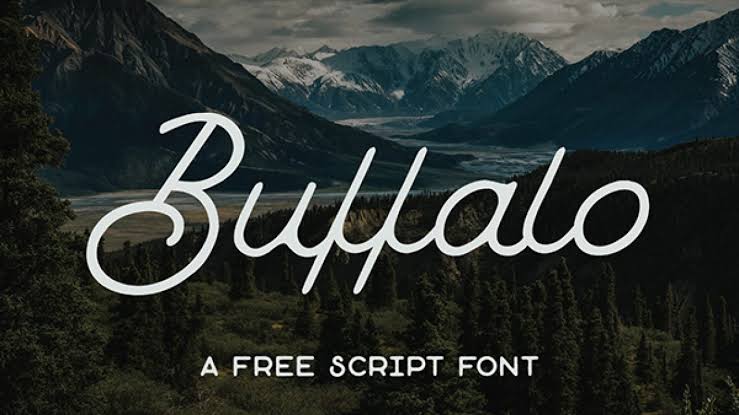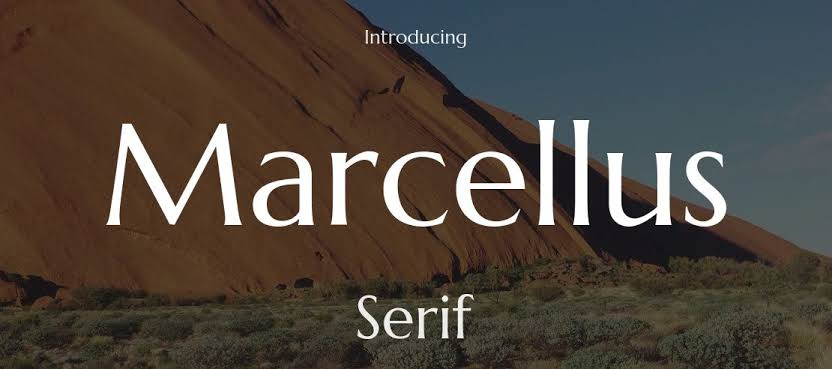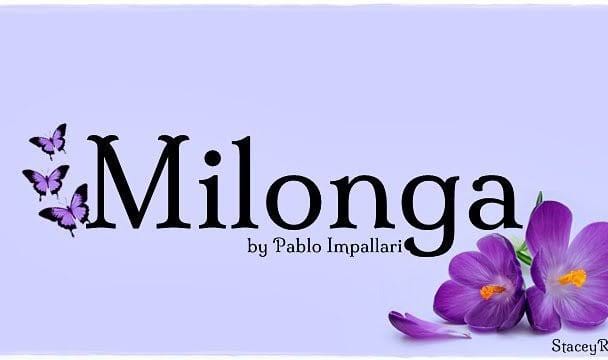
Untuk menciptakan visual yang menarik ada banyak pilihan gaya desain yang bisa digunakan seperti style desain boho. Berbicara soal style desain boho ini biasanya terkait dengan penggunaan elemen alam yang estetik. Dalam desain boho, tak hanya menggunakan warna alami, gambar dan pola dari alam tetapi juga font estetik yang relevan.
Desain tema boho dalam desain interior menciptakan kesan estetik dengan penggunaan bahan alami dan dekorasi alami. Sementara dalam desain grafis tema boho dapat menciptakan kesan gaya visual yang menggabungkan elemen visual bohemian. Gambar-gambar tumbuhan, elemen alam dan warna natural akan menciptakan kesan eksentrik, artistik dan bergaya bebas.
ELEMEN VISUAL DESAIN BOHO YANG UMUM
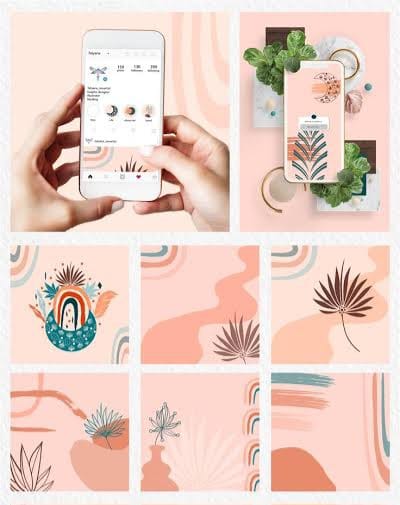
Untuk menciptakan gaya visual bertema boho dalam desain grafis gunakan elemen visual yang relevan. Secara umum desain grafis dengan style boho memiliki ciri elemen seperti:
Warna Hangat dan Natural
Desain grafis untuk tema boho jika diperhatikan identik dengan warna hangat seperti warna krem, coklat tua dan coklat muda. Terkadang juga menggunakan warna alami seperti warna hijau zaitun, terakota, oranye dan warna tanah. Kombinasi warna alam akan tampil harmonis, berkesan hangat dan alami.
Pola dan Tekstur Tradisional
Untuk digunakan sebagai dekorasi desain bergaya boho dapat menggunakan pola dan tekstur bergaya tradisional. Pola-pola etnik, geometris dan tribal dan motif bunga-bunga bisa menciptakan kesan vintage. Penggunaan pola dan tekstur bisa digunakan untuk dekorasi latar belakang secukupnya saja agar tidak berantakan.
Nuansa Vintage dan Ructik
Desain boho sering juga menggunakan simbol atau gambar tradisional dan kuno sehingga menciptakan nuansa vintage dan rustik yang menarik. Elemen tersebut akan menciptakan gaya vintage dan nostalgia yang menarik.
Elemen Gambar Alam
Gaya visual bertema boho juga kerap menggunakan gambar elemen alam seperti daun-daun, bulu, tekstur kayu, bunga dan gambar bunga dan matahari. Gambar matahari yang memiliki tampilan seperti simbol tradisional akan tampil estetik dan artistik.
Shapes Lembut dan Organik
Untuk penggunaan shapes dalam desain boho tidak menggunakan style yang kaku dan tajam. Tetapi menggunakan bentuk shapes organik yang lembut dan sudut yang tidak tajam. Bentuk yang melengkung dan lembut akan efektif menciptakan style desain yang estetik.
Font dan Teks Kasual
Gaya tipografi untuk desain grafis ini menggunakan style huruf yang unik dan terkadang eksentrik. Jenis font dengan gaya huruf yang ramah dan gaya tulisan tangan atau font bulat akan cocok dengan elemen alam. Penggunaan style huruf yang alam bertujuan untuk menciptakan tampilan desain yang organik dan alami.
REKOMENDASI FONT DESAIN BOHO
Berbicara soal penggunaan gaya font dalam desain boho ini biasanya memiliki ciri yang juga alami dan artistik seperti desain boho. Gaya font untuk desain boho kebanyakan memiliki ciri seperti:
- Berjiwa Bebas
- Artistik
- Rustik
- Unik
Untuk tema desain boho, font yang digunakan bisa mengambil berbagai jenis font termasuk serif, script dan display. Berikut beberapa rekomendasi font untuk desain boho:
Lancelot Font
Jenis font yang memiliki serif ini tampil klasik, magical dan unik karena beberapa hurufnya memiliki dekorasi memanjang terutama dalam variasi uppercase. Gaya desain boho dengan font ini akan tampil dan cocok dengan penggunaan elemen alam seperti bunga dan dedaunan. Font serif ini tampil lebih elegan dan mudah dibaca sehingga cocok untuk estetika desain boho.
Soria Font
Gaya font yang populer pada era klasik banyak ditemui dalam desain boho karena menciptakan kesan vintage. Penggunaan elemen visual dari pola-pola tradisional dan gambar seperti bunga dapat menciptakan kesan vintage.
Font bergaya vintage akan cocok dan seringkali dipilih. Font Soria ini juga memiliki serif dengan ujung bulat sehingga tampil ramah dan kasual. Gaya huruf pada font ini akan harmonis dengan elemen visual khas desain boho. Font yang juga disebut sebagai tipografi desain nouveau ini akan menciptakan desain yang lebih estetik.
Cherry Swash
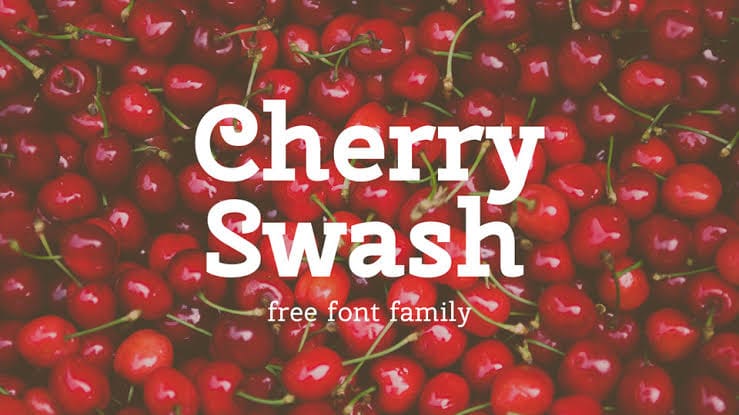
Gaya font serif ini tampil lebih unik dan nyentrik karena memiliki kombinasi seri yang menarik. Gaya slab serif yang tebal dan kotak menciptakan tampilan klasik dan formal. Gunakan font dalam variasi huruf yang tipis sehingga menciptakan tampilan tipografi yang ramah.
Beberapa huruf dalam font ini memiliki serif yang melengkung seperti ornamen klasik sehingga gaya ini menciptakan kesan tradisional. Gaya huruf yang juga tampil klasik ini akan relevan dengan elemen visual tradisional dan simbol kebudayaan dalam desain boho.
Saturday Champagne
Gaya font untuk desain boho juga bisa menggunakan style huruf latin atau bersambung dengan garis tipis. Huruf latin akan menciptakan tampilan visual yang alami karena font script mengikuti gerakan tulisan tangan. Gaya font ini juga dapat dikombinasikan dengan font serif klasik agar harmonis.’
Dalam menciptakan desain yang menarik, gunakan jenis font yang sesuai tema desain termasuk untuk gaya bho. Gaya boho yang identik dengan penggunaan elemen alam seperti gambar bunga, daun dan simbol matahari juga menggunakan warna terang yang hangat. Untuk jenis font yang identik dengan gaya desain boho gunakan beberapa style font tersebut yang tampil ramah, kasual dan estetik.